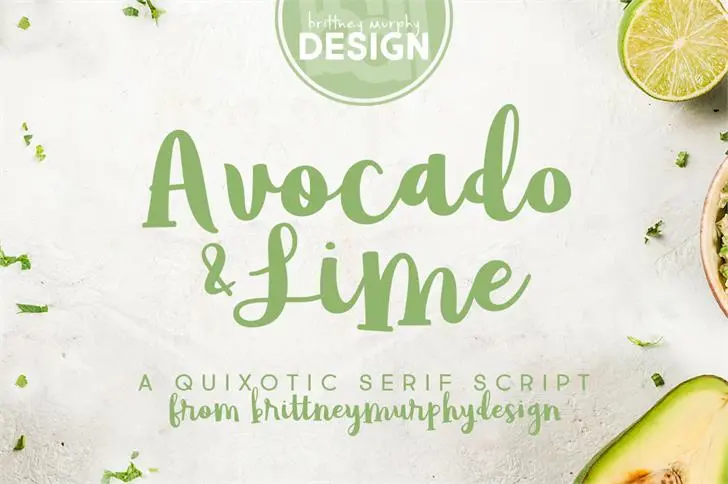
Avocado & Lime Script Font – Download Grátis
Boa tarde, estamos ansiosos para compartilhar com você a Avocado & Lime, uma nova escolha no universo das fuentes script. Este bold e quixótico conjunto de caracteres serifos foi projetado por Brittney Murphy Design. A fonte oferece um toque especial: ligaturas abertas, alternativas estilizadas e contextualizadas, além de swashes incríveis que garantem movimento e originalidade em qualquer projeto. Ideal para uso em impressões, logotipos, marcações ou qualquer outro projeto criativo que você possa imaginar, a Avocado & Lime é certamente um atalho para tornar seu trabalho mais encantador e deslumbrante. Seja uma escolha inspiradora para seus próximos projetos gráficos.